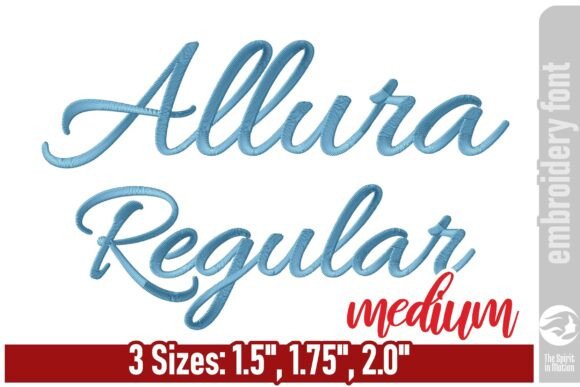
Allura Script Embroidery Font - Medium
Mencari elemen reka bentuk yang sesuai boleh menjadi mencabar, tetapi Allura Script Embroidery Font - Medium menawarkan koleksi luar biasa yang menaik taraf karya anda serta-merta.
Sama ada anda mencipta produk POD (Print on Demand), jemputan perkahwinan atau grafik media sosial, Allura Script Embroidery Font - Medium amat bersesuaian.